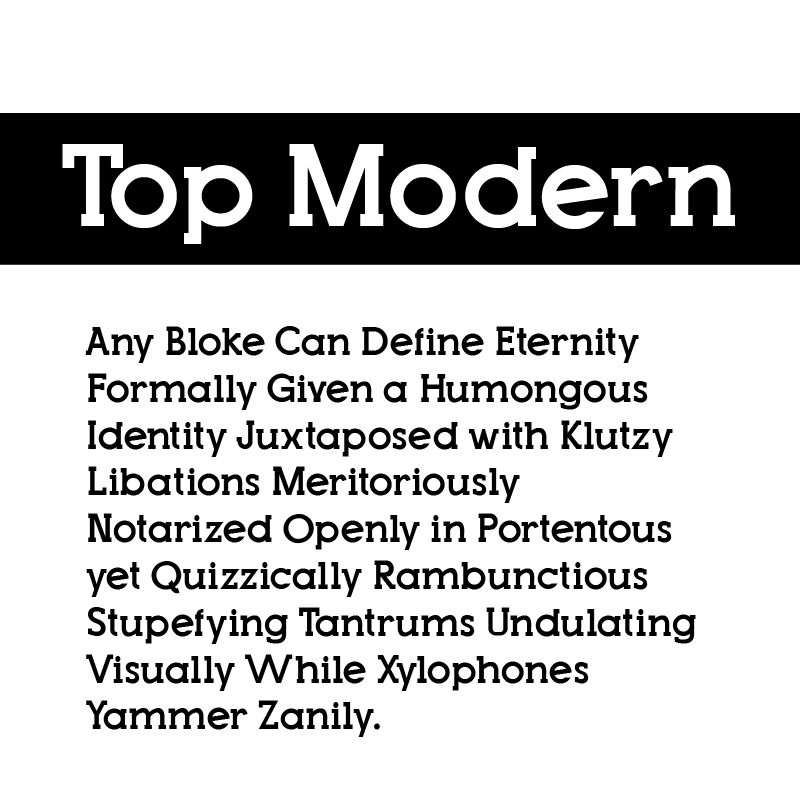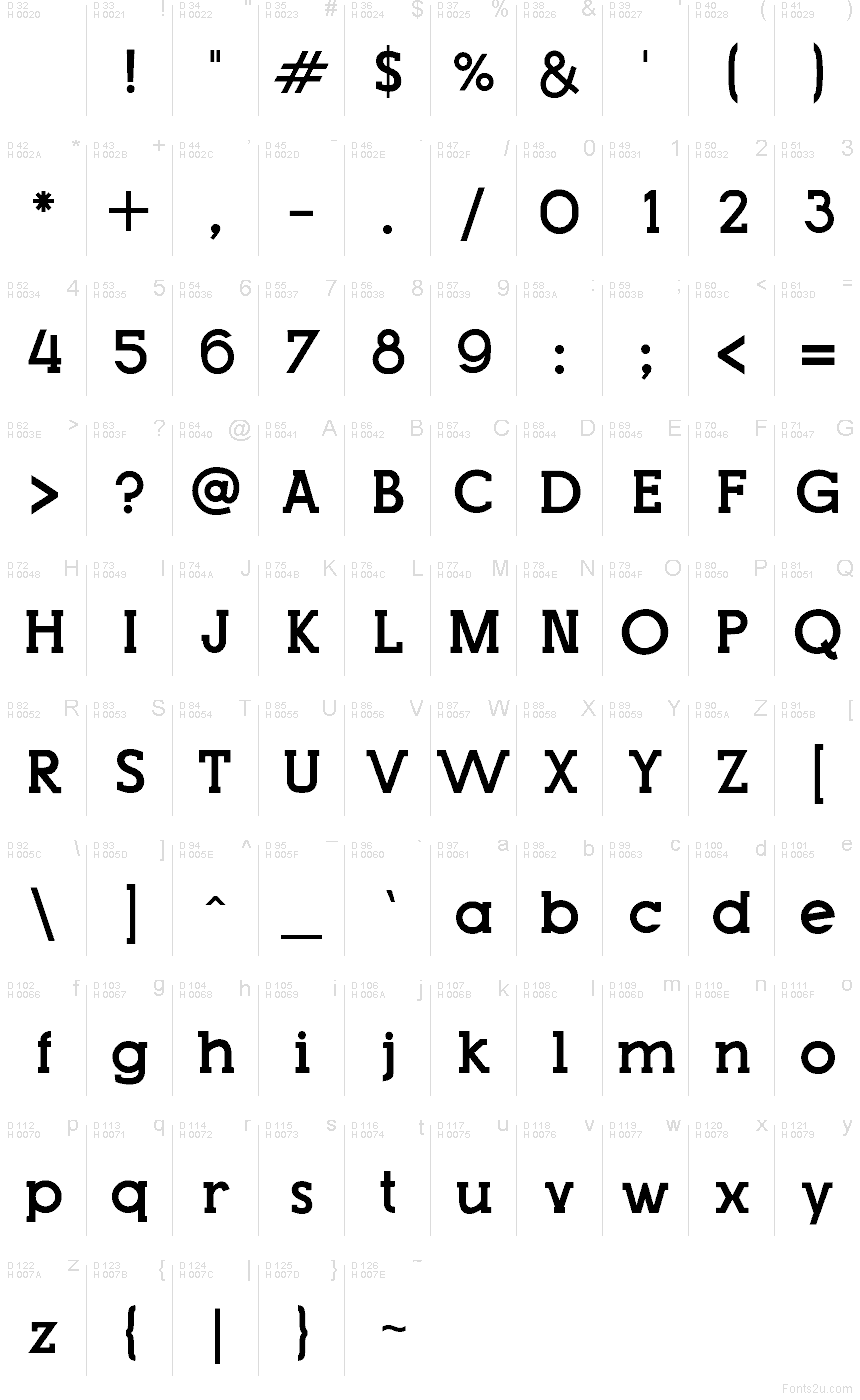
Top Modern von Galdino Otten Fonts ist eine kostenlose, fette Serifenbetonte mit übergroßen Formen und einer präzisen architektonischen Silhouette. Breite vertikale Striche, quadratische Serifen und fast kreisrunde Rundungen verleihen dem Schriftbild ein kompaktes, kraftvolles Profil.
Modelabels und Wohnmarken können sie für Logos, Verpackungen und Poster einsetzen, wo ihre an Papierschnitt erinnernde Solidität direkt und bewusst wirkt. Ihre solide Geometrie eignet sich auch für redaktionelle Cover, bei denen die Buchstaben mit beschnittener Fotografie oder einfachen Musterblöcken als Teil des Bildes und nicht nur als Bildunterschrift interagieren.